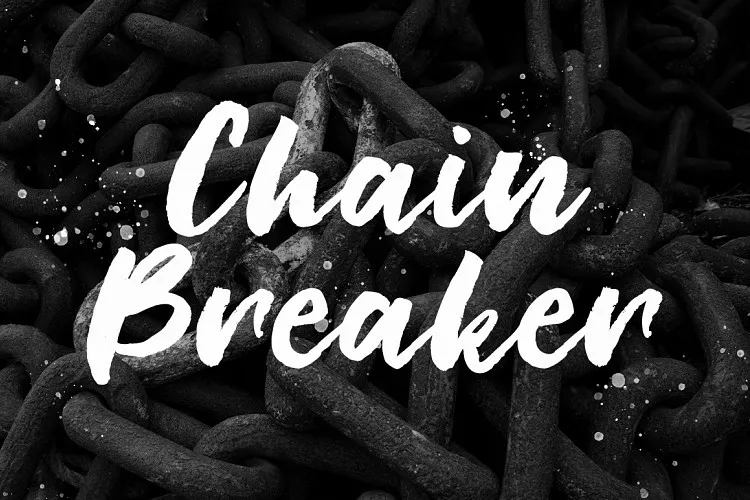
Chain Breaker Script Font – Download Grátis
Bem-vindo! Estamos entusiasmados para apresentar a você uma nova adição à nossa vasta seleção de fontes, chamada Chain Breaker Font. Desenvolvida por Uloel Design, esta é uma fonte feita à mão com um canuto de tinta, como letras de água colorida real. O estilo desse design permite que você combine a fonte com estampas e texturas d’água, textos no fundo – para alcançar o efeito natural mais perfeito. Criada com uma ferramenta de canudo suave, Chain Breaker Script Font tem um inicial característico excepcional e apresenta uma aparência única e atraente. Ideal para os vários designs pessoais que você pode criar em sua própria forma – desde roupas até identidades corporativas, t-shirts, embalagens, cartões de visita, entre outros.